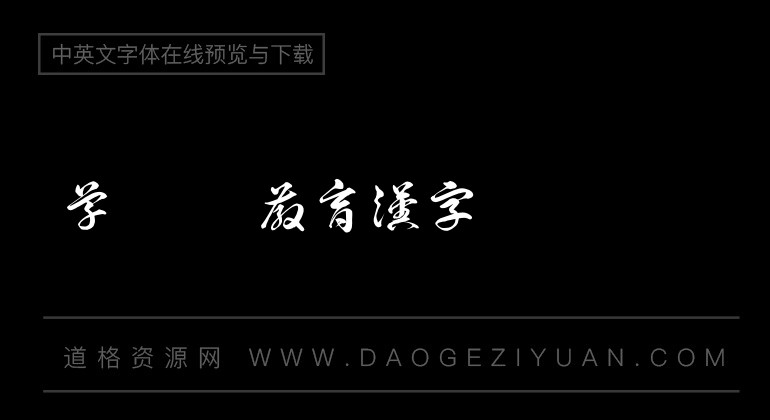
草龍OTF教育漢字字体是一种专门设计用于教育领域的汉字字体。它采用了草书风格,字形简洁明了,线条流畅自然,让学生更容易理解和掌握汉字的结构和笔画。此外,草龍OTF教育漢字字体还具有多种字重和字形,能够满足不同学科和场合的需求,例如课本、作文、海报等。该字体还支持跨平台应用,可在Windows、Mac、iOS和Android等操作系统上使用。总之,草龍OTF教育漢字字体是一个优秀的教育工具,为学生提供了一个高质量、方便使用和易于理解的汉字学习环境。文件名:草龍OTF教育漢字
草龍OTF教育漢字是一款非常不错的手写艺术字体,具有很好的视觉感,适合于文化类的宣传设计、商业类品牌的广告和产品包装设计以及个性化文字排版等较多场景。